멋진 싸인은 하루아침에 만들어지는 것이 아니에요. 꾸준한 연습을 통해 자연스럽고 완성도 높은 싸인을 만들 수 있죠. 싸인을 더 멋지게 보이게 하려면 어떤 연습이 효과적인지 알아볼까요? 🚀
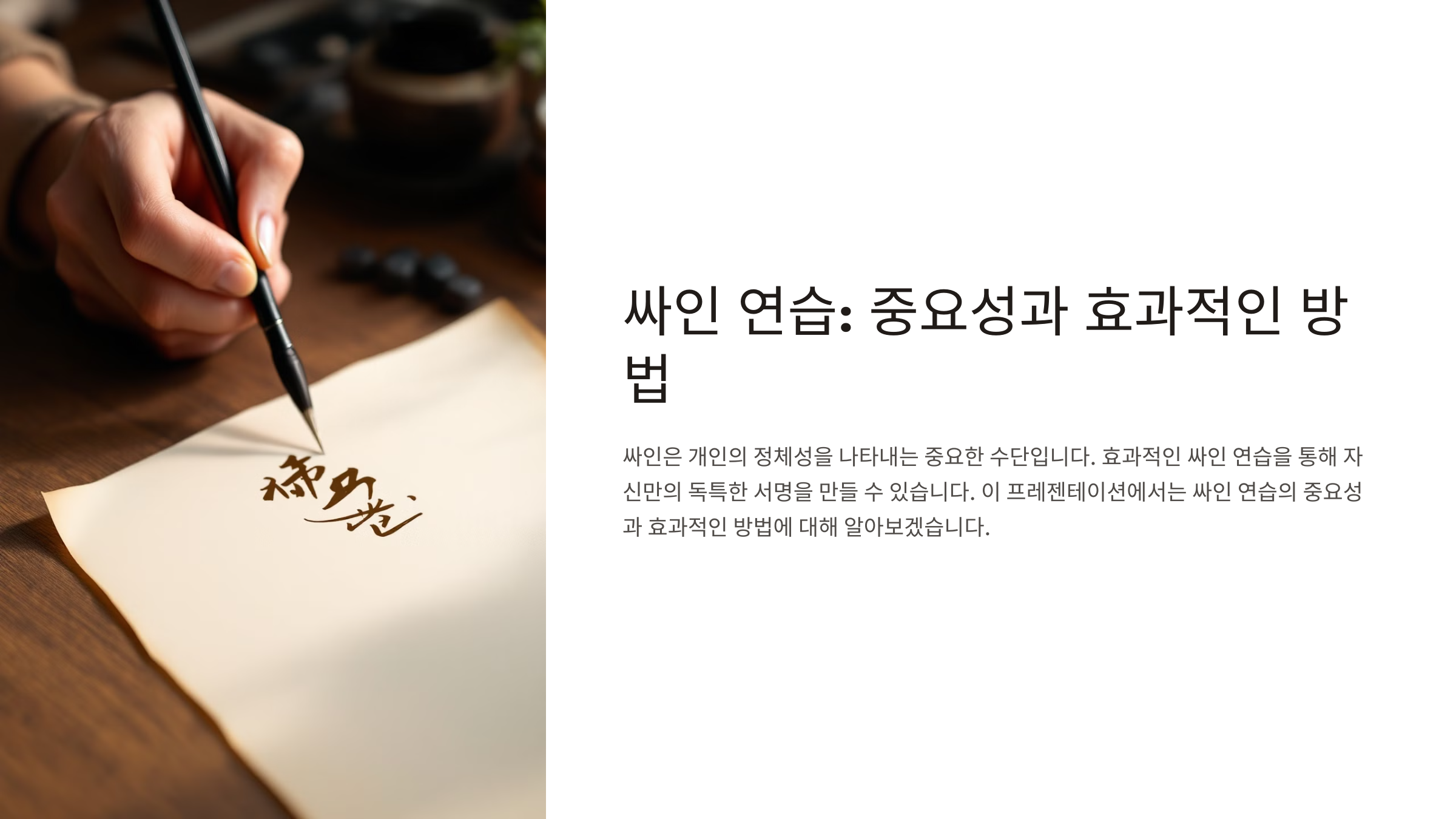
싸인 연습이 중요한 이유 ✨
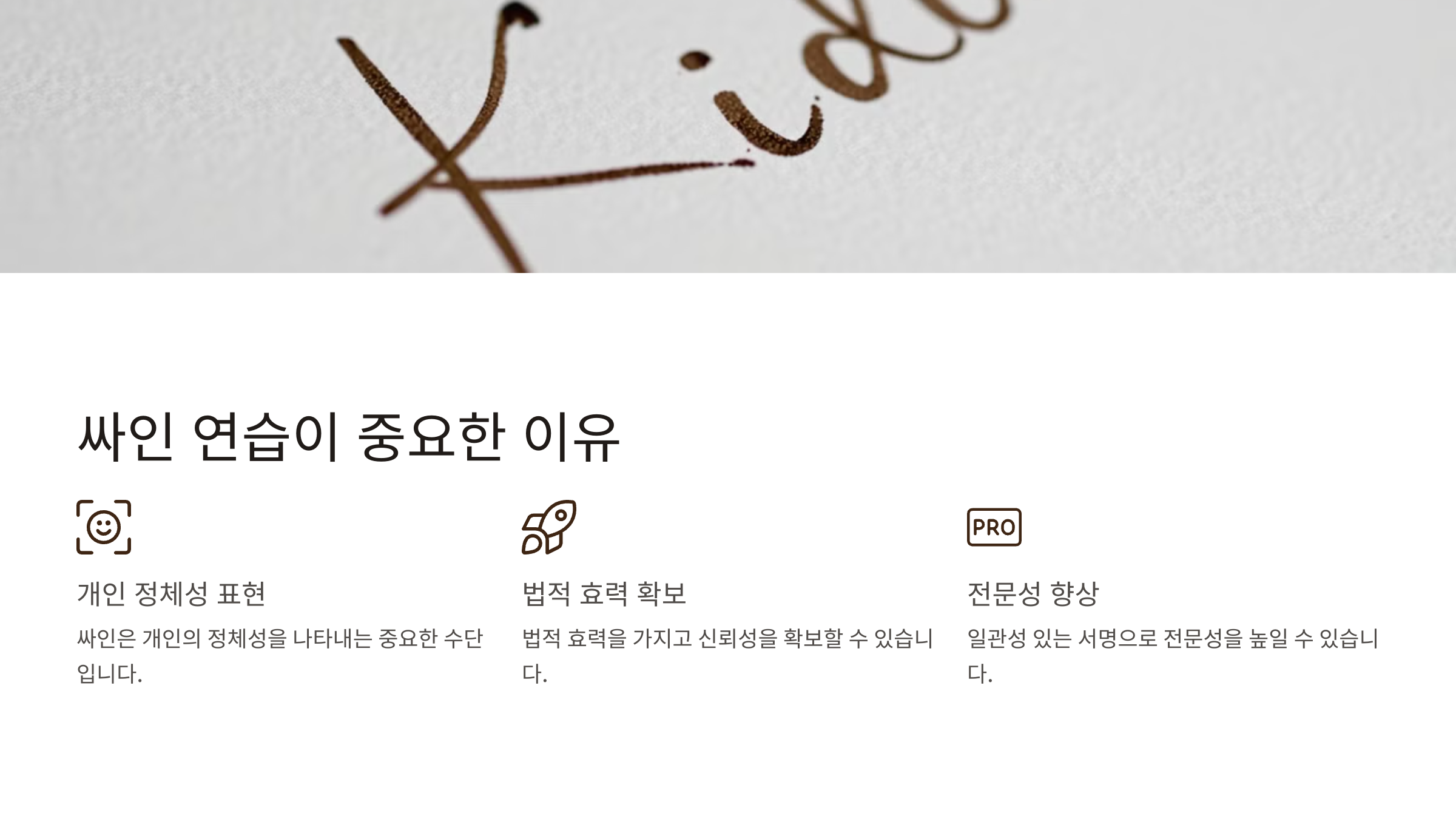
싸인은 단순한 서명이 아니라, 자신을 나타내는 상징적인 요소예요. 꾸준한 연습을 통해 싸인을 개선하면 더 세련되고 자연스러운 싸인을 만들 수 있어요.
📌 꾸준한 싸인 연습이 필요한 이유 💡
이유 설명 자연스러움 연습을 많이 할수록 싸인이 손에 익어 부드럽게 나와요. 일관성 유지 자주 사용해야 같은 스타일을 유지할 수 있어요. 빠른 작성 가능 속도가 빨라지면 실생활에서도 편리해져요. 개성 표현 꾸준한 연습을 통해 더 개성 있는 싸인을 만들 수 있어요. 이제 싸인의 중요성을 알았으니, 기본적인 싸인 연습법을 알아볼까요? ✍
기본적인 싸인 연습법 ✍
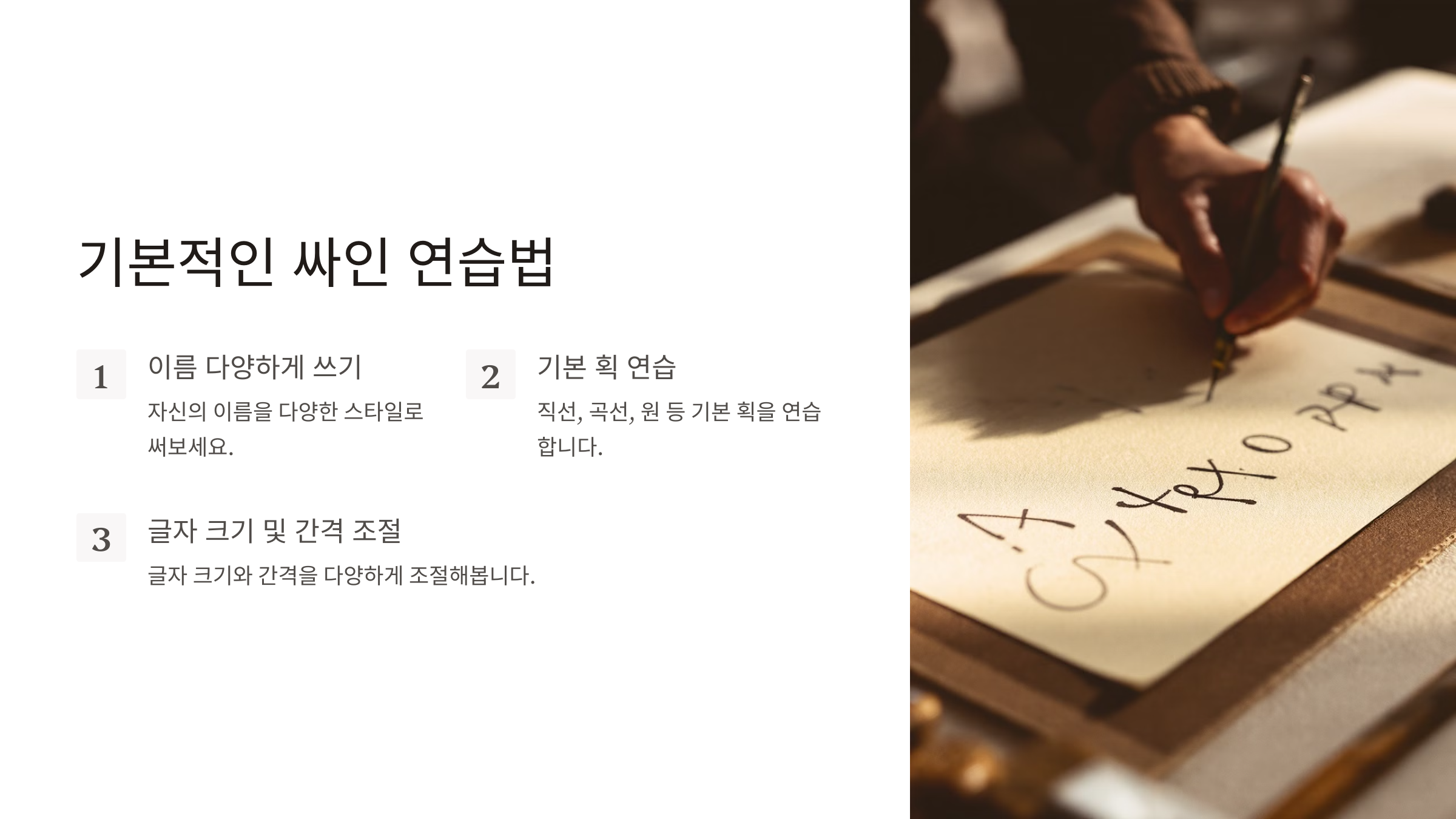
싸인 연습은 처음부터 너무 복잡하게 할 필요 없어요. 가장 중요한 것은 자연스럽고 빠르게 쓸 수 있도록 연습하는 것이에요. 처음 시작하는 분들을 위해 기본적인 연습법을 알려드릴게요! 🚀
📌 싸인 연습을 위한 3단계 기본법 🎯
단계 설명 STEP 1: 기본 형태 연습 이름을 여러 번 써보면서 가장 자연스러운 형태를 찾아요. STEP 2: 속도 조절 처음에는 천천히 연습하고 점점 빠르게 써봐요. STEP 3: 반복 연습 하루 5~10분씩 꾸준히 연습하면 손에 익어요. 이제 기본적인 연습 방법을 알았어요! 그럼 싸인의 스타일을 살리는 연습법을 알아볼까요? 😊
스타일을 살리는 싸인 연습법 🎨
싸인은 단순히 이름을 적는 것이 아니라, 개성과 스타일을 표현하는 도구예요. 그럼 싸인을 더 세련되고 스타일리시하게 보이게 하려면 어떻게 해야 할까요? 🤔
💡 싸인 스타일을 살리는 3가지 방법 ✨
- 기울기 조절 → 오른쪽으로 살짝 기울이면 역동적인 느낌을 줄 수 있어요.
- 획의 굵기 변화 → 글자의 일부를 두껍게 하면 개성 있는 스타일이 완성돼요.
- 특별한 기호 추가 → 점 . , 밑줄 __ , 별 ⭐ 등을 활용하면 포인트가 돼요.
이제 스타일을 살린 싸인을 만들었어요! 그럼 빠르고 자연스러운 싸인을 만들려면 어떻게 해야 할까요? 🚀
빠르고 자연스러운 싸인을 만드는 법 ⚡
싸인은 빠르게 쓰면서도 알아보기 쉬운 것이 가장 좋아요. 너무 오래 걸리는 싸인은 실생활에서 사용하기 어려울 수 있어요.
📌 빠르고 자연스러운 싸인을 위한 3가지 팁 🔥
- 📍 이니셜 활용 → 이름 전체 대신 이니셜을 강조하면 빠르게 쓸 수 있어요.
- 📍 연결선 사용 → 글자 사이를 연결하면 자연스럽게 흐르는 싸인이 돼요.
- 📍 짧고 강렬한 마무리 → 마지막 획을 강조하면 인상적인 싸인이 돼요.
이제 싸인 연습이 점점 쉬워지고 있어요! 그럼 싸인을 연습할 때 어떤 도구를 사용하면 좋을까요? ✍
싸인 연습을 위한 도구 추천 🖊
좋은 도구를 사용하면 싸인 연습이 더욱 쉬워져요. 다양한 펜과 종이를 활용하면 싸인을 더 세련되게 만들 수 있답니다! 😊
🛠 싸인 연습에 좋은 도구 3가지
- 🖋 만년필 → 획의 굵기 변화를 쉽게 줄 수 있어요.
- 🖊 볼펜 → 실생활에서 가장 자주 사용하는 필기구예요.
- 📄 그리드 노트 → 정렬을 맞추면서 연습할 수 있어요.
좋은 도구를 사용하면 연습이 더 효과적이겠죠? 하지만 연습할 때 피해야 할 실수도 알아야 해요! ⚠
싸인 연습할 때 피해야 할 실수 ❌
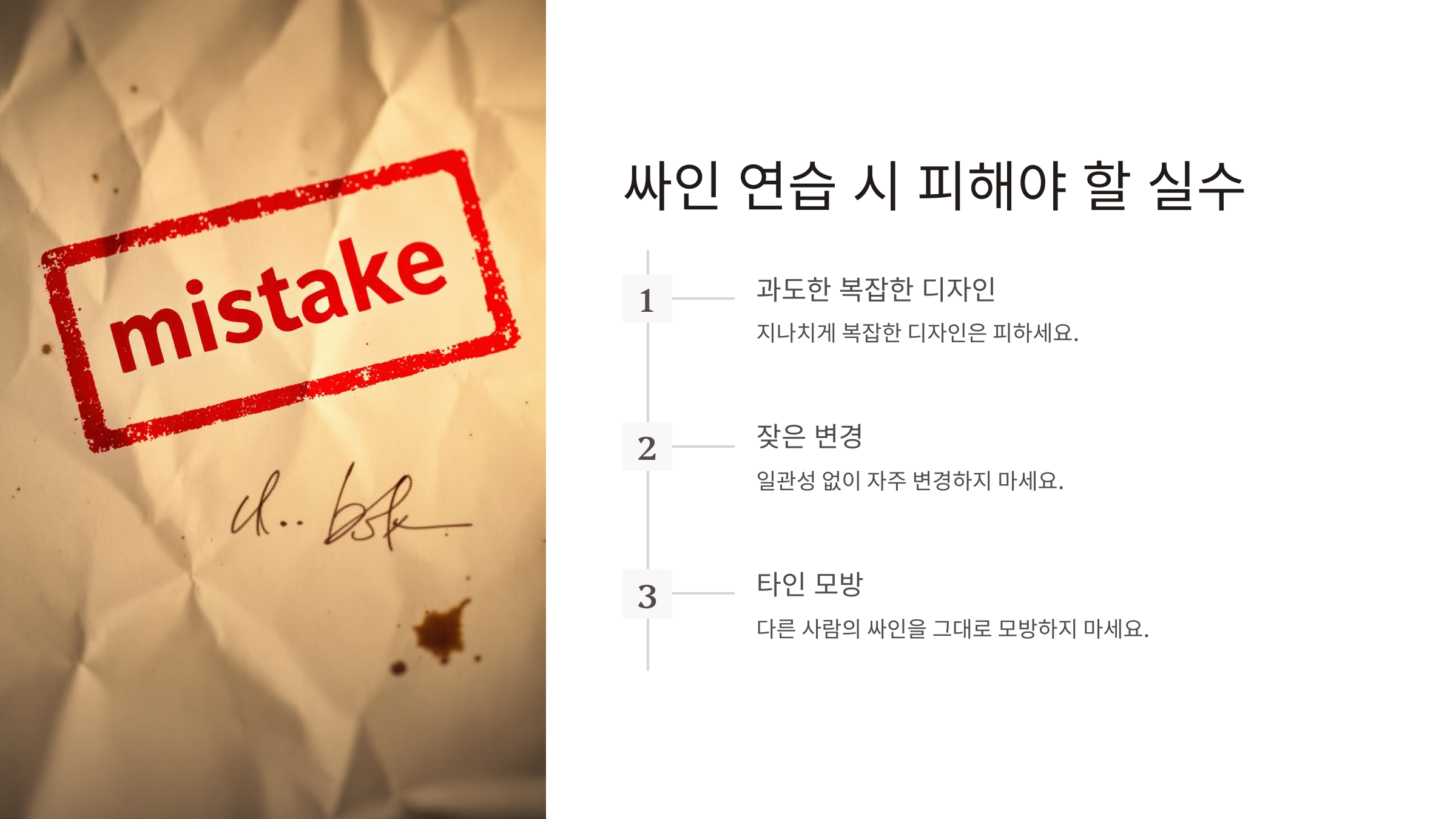
싸인 연습을 하면서 잘못된 습관이 생길 수도 있어요. 그럼 싸인 연습할 때 피해야 할 실수들을 알아볼까요? 🤔
🚫 피해야 할 싸인 연습 실수 3가지
- ❌ 너무 복잡한 싸인 만들기 → 사용하기 불편할 수 있어요.
- ❌ 획이 일관되지 않음 → 싸인 스타일이 일정해야 해요.
- ❌ 너무 힘줘서 쓰기 → 부드럽게 쓰는 연습을 해야 해요.
이제 싸인 연습의 모든 것을 알았어요! 마지막으로 싸인 연습과 관련된 FAQ를 살펴볼까요? ❓
FAQ ❓
Q1. 싸인 연습은 하루에 얼마나 해야 하나요?
A1. 하루 5~10분 정도 연습하면 자연스럽게 손에 익어요. 꾸준히 연습하면 몇 주 안에 멋진 싸인을 완성할 수 있어요! ✍
Q2. 싸인을 쉽게 변경해도 괜찮을까요?
A2. 네, 싸인은 자유롭게 바꿀 수 있어요. 하지만 공식 문서에 사용하는 싸인은 일관성 유지가 중요해요. 자주 변경하면 신분 확인이 어려울 수도 있어요. ⚠
Q3. 싸인 연습을 할 때 볼펜이 좋을까요, 만년필이 좋을까요?
A3. 연습할 때는 볼펜과 만년필을 번갈아 사용하는 것이 좋아요! - 🖊 볼펜: 실생활에서 자주 쓰이는 필기구라 익숙해져요. - 🖋 만년필: 획의 굵기를 조절하며 스타일을 만들 수 있어요. 두 가지 도구로 연습하면 더 다양한 싸인을 만들 수 있어요! 😊
Q4. 싸인이 너무 복잡한데, 간단하게 바꾸는 방법이 있나요?
A4. 싸인이 너무 복잡하면 간결한 스타일로 변형해 보세요! - 🔹 이니셜 활용: 이름의 첫 글자만 강조해보세요. - 🔹 연결선 추가: 글자를 부드럽게 이어 쓰면 단순해져요. - 🔹 기울기 조정: 약간의 기울기로 스타일을 더할 수 있어요. 이렇게 하면 더 빠르고 멋진 싸인을 만들 수 있어요! 😆
Q5. 싸인 연습을 오래 하면 손이 아픈데, 해결 방법이 있나요?
A5. 네, 손이 아프지 않게 하기 위해 힘을 빼고 부드럽게 쓰는 연습을 해보세요! 또한, 싸인을 연습할 때 다양한 펜을 사용해 보는 것도 좋아요. 너무 오래 연습하지 말고 5~10분 간격으로 쉬어가면서 연습하세요! ⏳
Q6. 싸인을 예쁘게 만드는 가장 쉬운 방법은?
A6. 싸인을 예쁘게 만들고 싶다면 이 3가지를 기억하세요! ✅ 획의 일관성: 같은 두께와 스타일을 유지하세요. ✅ 간결한 디자인: 너무 복잡하지 않게 간단한 형태를 만드세요. ✅ 특별한 포인트: 밑줄, 점, 기울기 등을 추가해보세요. 이 세 가지만 지켜도 싸인이 훨씬 멋져 보여요! 🎨
Q7. 싸인 연습을 하면 필체도 좋아질까요?
A7. 네! 싸인을 연습하다 보면 손글씨가 더 깔끔해질 수 있어요. 글자의 균형을 맞추는 연습이 되기 때문에 필체 개선에도 도움이 돼요! 📖
Q8. 싸인을 더 개성 있게 만들고 싶어요. 어떻게 해야 할까요?
A8. 싸인에 개성을 더하는 방법은 여러 가지가 있어요!
✅ 기호 추가: 별 ⭐, 점 . , 밑줄 __ 등을 활용하세요.
✅ 획 강조: 글자의 특정 부분을 굵게 써보세요.
✅ 이니셜 변형: 글자 일부를 변형하면 독창적인 느낌을 줄 수 있어요. 이런 작은 변화만 줘도 더 개성 있고 특별한 싸인을 만들 수 있어요! 😍
싸인은 단순한 서명이 아니라 자신만의 개성을 표현하는 요소예요. 자연스럽고 세련된 싸인을 만들려면 꾸준한 연습과 올바른 방법이 중요해요. 이번 글에서 배운 연습법을 활용해 더 멋지고 스타일리시한 싸인을 만들어보세요! 🚀